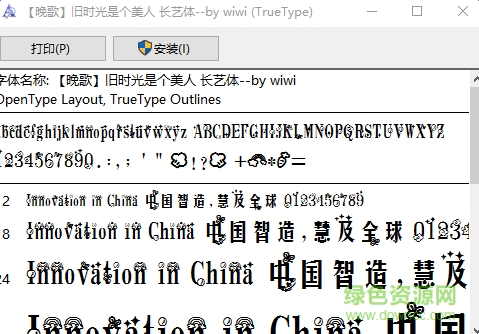
舊時光是個美人字體是一款很好看的電腦個性字體,這款字體寫出來的字是很美觀的,而且有著別的字體沒有的魅力,相信很多朋友們都會喜歡這款字體的,歡迎有需要的朋友來綠色資源網(wǎng)下載。
舊時光是個美人字體是真的很不錯,因?yàn)槠洫?dú)特的魅力,用于藝術(shù)方面是最合適不過的,喜歡的朋友可以隨時來綠色資源網(wǎng)下載。